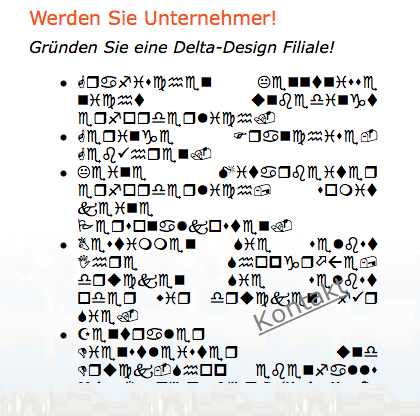
Man kann sogar Franchisen und das ganz ohne was von Gestaltung zu verstehen … ich frag mich wie das gehen soll …
Das ist doch genau erklärt:
Steht das bei dir wirklich so? Denn ich kann zum Beispiel lesen, das „grafischen Kenntnissen“ nicht nötig sind, um Grafiker zu werden … so gesehen, kann ich mich dann jetzt auch direkt wieder exmatrikulieren und müsste irgendwas tun, um zu vergessen, was ich hier im Forum von euch gelernt hab :hammer:
wer noch mehr von diesx «KünstlerIn» sehen will …
Und da beschäftigt man sich so sehr mit einem eigenen Logo und Webseite und und und ...
... einfach franchisen und gut – so einfach hätt’ ich’s haben können  :party:  :hammer:
Aber wenigstens hat das KünstlerIn das Betätigungsfeld Tattiii (noch) nicht für sich entdeckt. Da könne er ja auch noch das Neveau richtig steigern :-)
Wenn der so Puppen spielt, wie er gestaltet, sollte man das besser verbieten :hammer: ich hab jetzt nicht geschaut: kann man das Puppen-Ding auch franchisen?